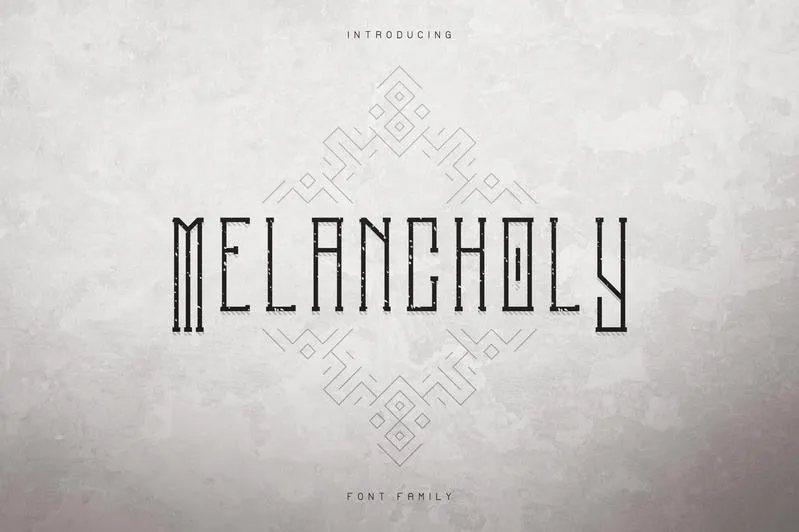
Melancholy Display Font + Extra – Download Grátis
A fonte “Melancholy Display Font + Extra” é uma tipografia gótica longa com cinco tipos de fontes, elementos vetoriais e suporte multilíngue. Esta fonte está equipada para trabalhar bem tanto nos textos grandes quanto em versões menores. Seu design elegante se destaca na categoria de fonts góticas. É perfeitamente adequada para a criação de materiais gráficos variados, como logotipos, cartazes e letras do painel. Além disso, a inclusão dos elementos vetoriais permite que você personalize ainda mais seu trabalho em uma variedade de formatos de imagem e design digital. Essa fonte é um excelente escolha para aqueles que procuram um elemento único e moderno em seus projetos gráficos. Com suporte multilíngue, ela também pode atender a necessidades internacionais sem complicação. Para designers apaixonados pela tipografia gótica ou simplesmente buscando uma fonte única, “Melancholy Display Font + Extra” é um investimento de qualidade que não irá decepcionar.